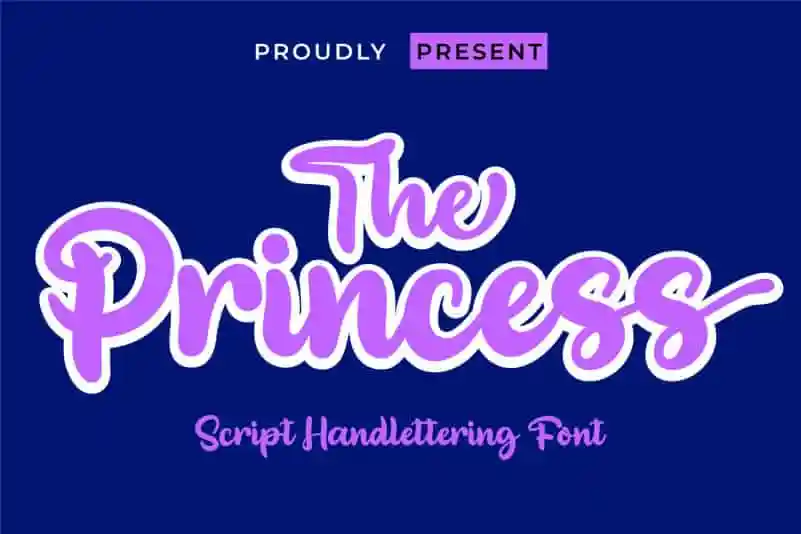
The Princess Script Font – Fonte Grátis
The Princess Script Font
A fonte ‘The Princess Script Font’ é perfeita para projetos de design que exigem uma escrita elegante e harmoniosa, com suas curvas suaves e linhas fluidas que se moldam ao texto de maneira incrível. Este recurso de tipografia garante um estilo sofisticado, ideal tanto para aplicativos pessoais quanto para grandes propostas visuais. Se você está buscando uma fonte de escrita perfeita para design gráfico e criação visual, ‘The Princess Script Font’ é a escolha ideal. Suas linhas curvadas elegantes permitem que você crie designs variados como convites para casamentos, anúncios publicitários, promoções para alimentos e bebidas em banners, assinaturas, cartazes de eventos sociais e muito mais. Este é um recurso de tipografia perfeito tanto para projetos profissionais quanto para aqueles que valorizam um toque artesanal na sua identidade visual.